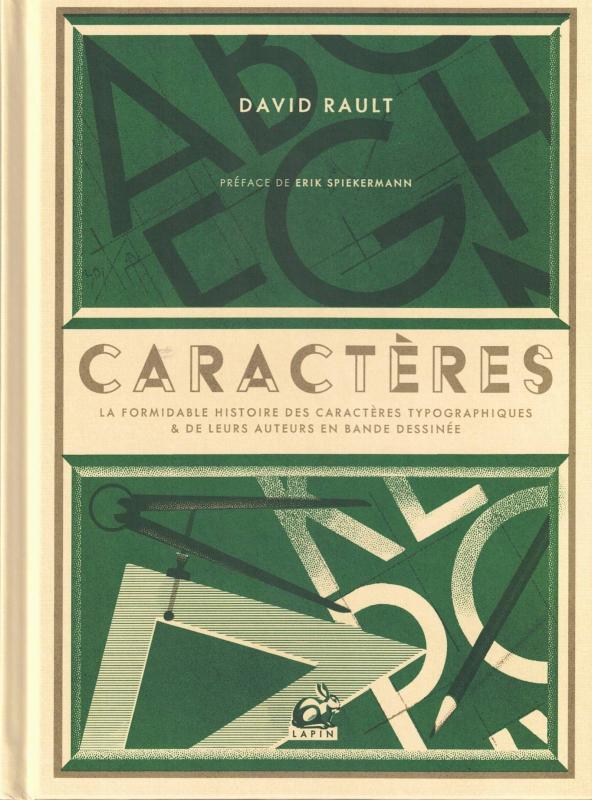
CARACTèRES
Livre neuf. Caractères. David Rault raconte l'histoire des caractères typographiques et de leurs concepteurs en bande dessinée. Vous connaissez ces caractères, que l'on retrouve partout dans les logos des grandes sociétés, les packagings, les logiciels informatiques... et maintenant David vous montre commente ces femmes et ces hommes ont forgé le design de notre société moderne.